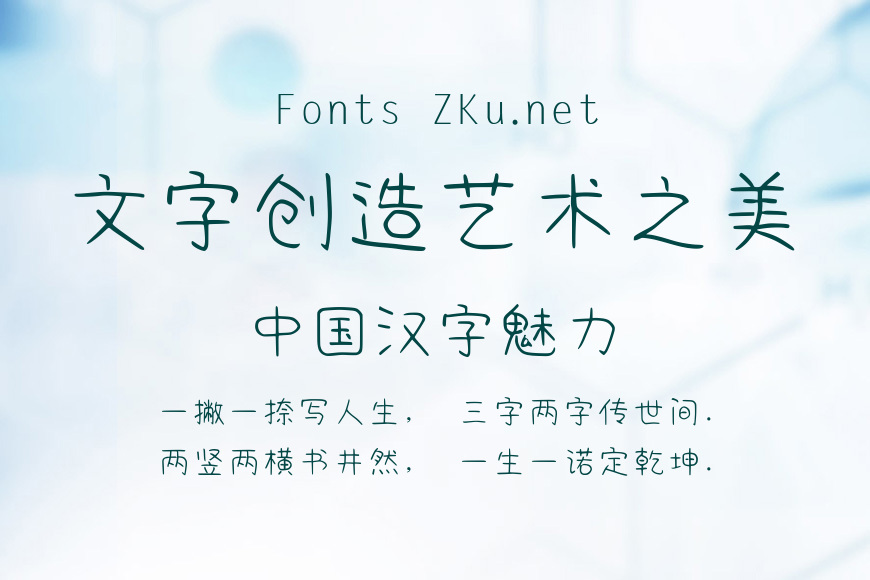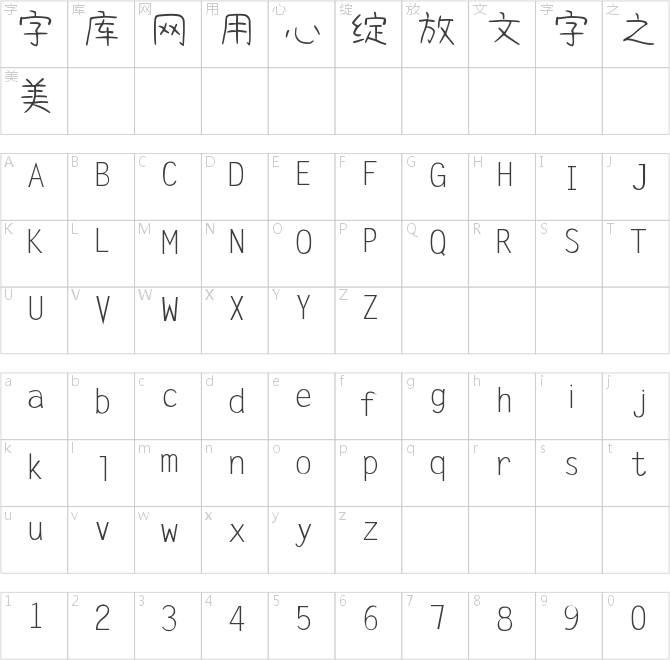
字体名称: 礼品卉自由理想
礼品卉自由理想体
既然是自由体嘛,那就要洒脱一些,没有那么多的规矩;本该横的地方,它横得没那么直,本该竖的地方,它又竖得没那么利索;有点像你在家里躺在沙发上看电视剧的姿势,“葛优躺”见过吗?嗯,就那样;凡是框框的地方,都用圈圈代替,比如《品》字,画三个圈圈祝福你,直到永远!